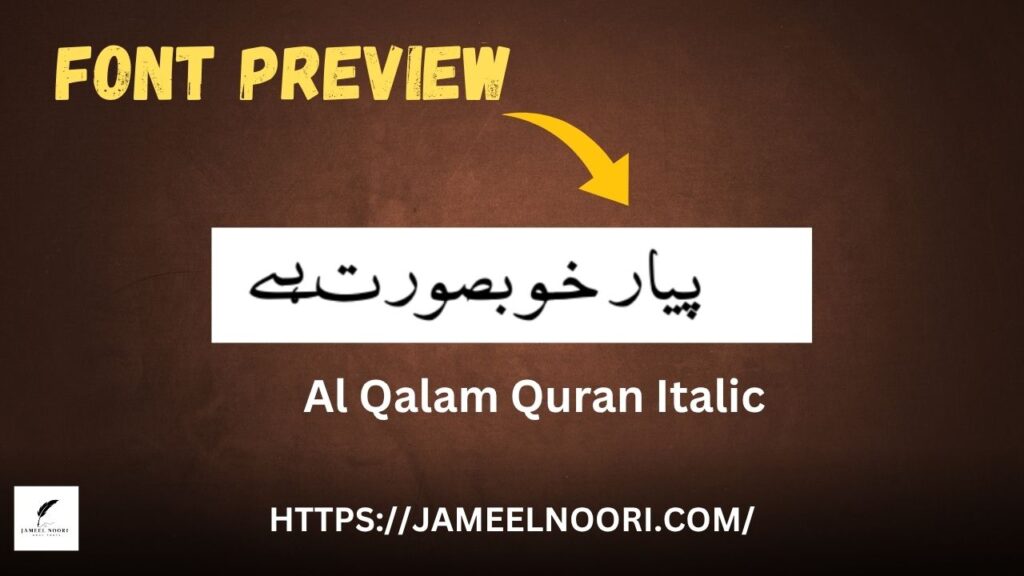
Urdu Font Al Qalam Quran Italic ek mashhoor aur khubsurat Italic TrueType Font hai jo specially Quranic aur Urdu calligraphy ke liye design kiya gaya hai. Ye font na sirf graceful look deta hai balki text ko ek classic Arabic-style touch bhi provide karta hai. Is article me hum apko is font ke bare me complete information dy gy taki aap bina time waste kiye is font ka best use kar saken.
What is Urdu Font Al Qalam Quran Italic?
Urdu Font Al Qalam Quran Italic ek Islamic-style Urdu font hai jo readability aur elegance dono offer karta hai. Ye font designers aur students dono ke liye best choice hai, khas tor par jab baat Quranic text ya Urdu headings likhne ki hoti hai.
Is font ka style thoda slanted italic type hai jo isay ek unique look deta hai aur readers ke liye visually appealing banata hai.
Features of Urdu Font Al Qalam Quran Italic
Is font ke kuch amazing features ye hain:
- Beautiful Italic Style – Quranic aur artistic look ke liye perfect.
Best Uses of Urdu Font Al Qalam Quran Italic
Ye font specially Quranic aur Islamic content ke liye banaya gaya hai. Lekin isko aap different projects me bhi use kar sakte hain:
- Quran aur Arabic text design karne ke liye
- Urdu poetry aur Islamic quotes likhne ke liye
- Educational materials aur digital banners banane ke liye
Why Choose Urdu Font Al Qalam Quran Italic (Expert Choice)
Urdu Font Al Qalam Quran Italic un logon ke liye ideal hai jo apne Urdu text me Islamic elegance chahte hain. Ye font visually balanced, easily readable, aur design ke hisab se perfect hai.
Iska italic style aapke design ko ek professional aur graceful feel deta hai — jise designers aur calligraphers Pakistan, Lahore, aur Karachi me widely use karte hain.
What makes this font different from others?
Its italic Quranic calligraphy style makes it stand out among Urdu fonts.